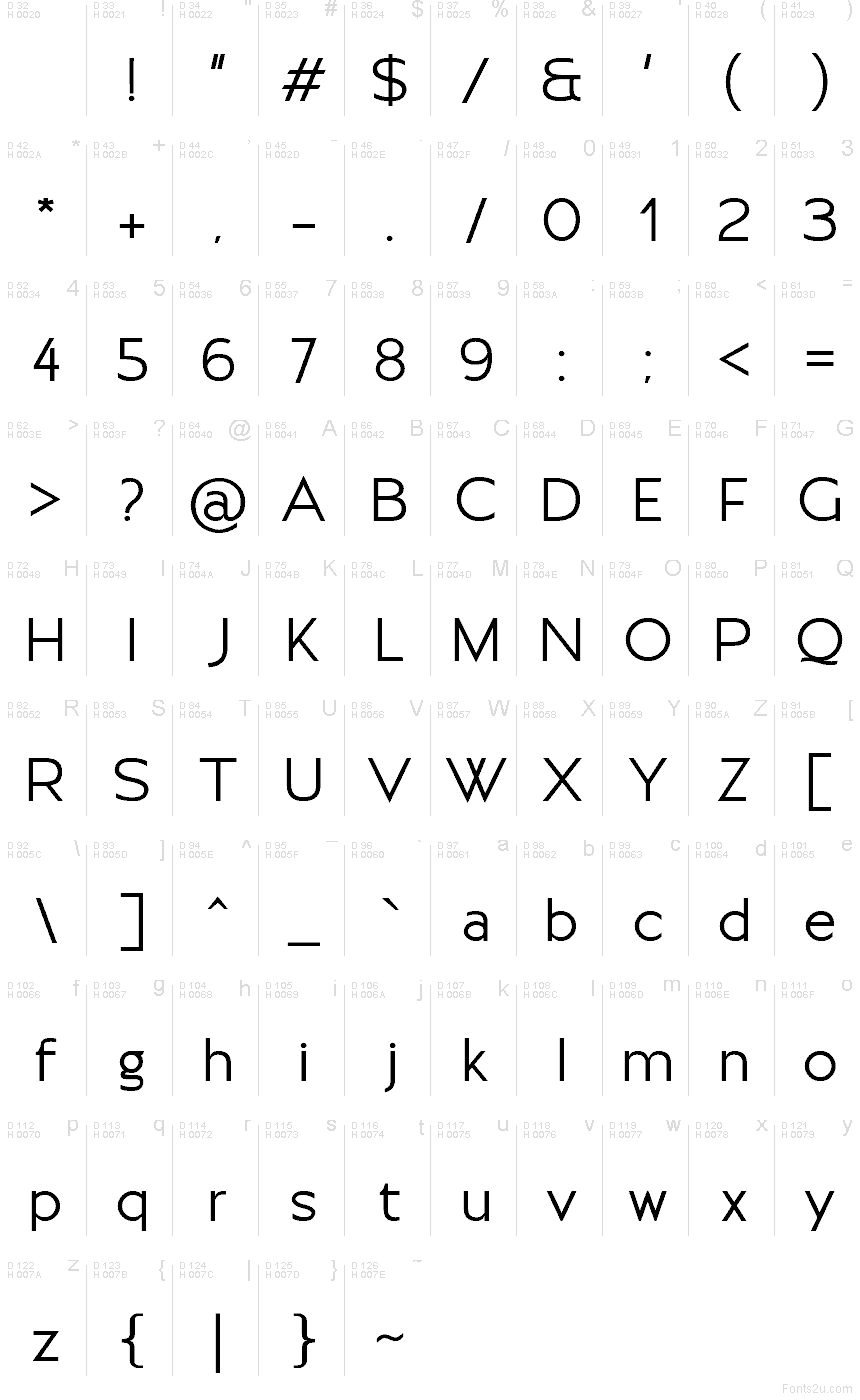
Písmo Moirest od Muhamada Fikryho Nuralifa z Fikryal Studio je minimalistické bezpatkové písmo, jehož vlasové tahy dodávají textu klid a eleganci jako v galerii umění. Díky širokému, vzdušnému prostrkání a ostré geometrii zůstává skvěle čitelné, přičemž působí téměř beztížně – jako by bylo nakresleno technickým perem.
Použití písma Moirest v lookbooku, na obalech kosmetiky, módních štítcích, plakátech do galerií, v nadpisech UI nebo stylových prezentacích dodá designu vytříbený tón bez zbytečného křiku. Nastavte jej o něco větší, než je běžné, a dejte mu dostatečné řádkování, aby vynikl jeho lehký rytmus. Toto bezplatné písmo kombinujte s hřejivým patkovým písmem nebo neutrálním groteskem pro hlavní text.